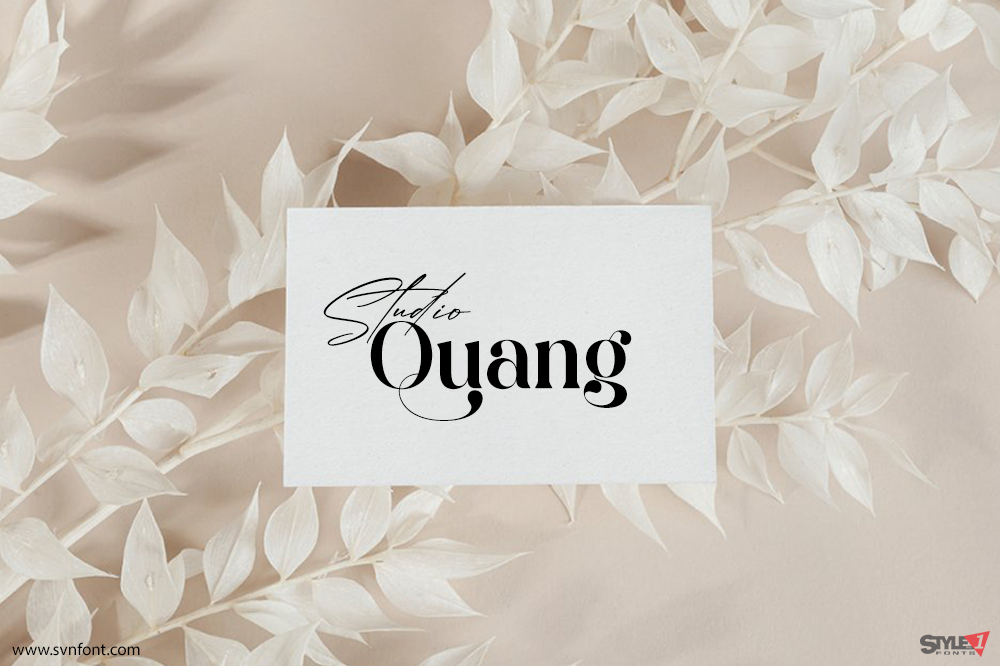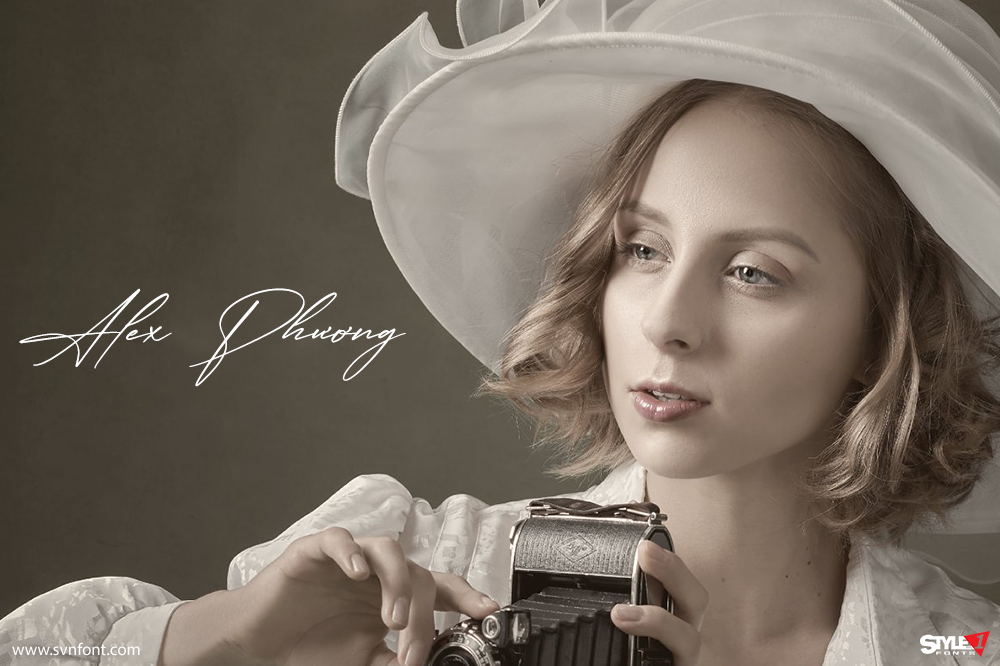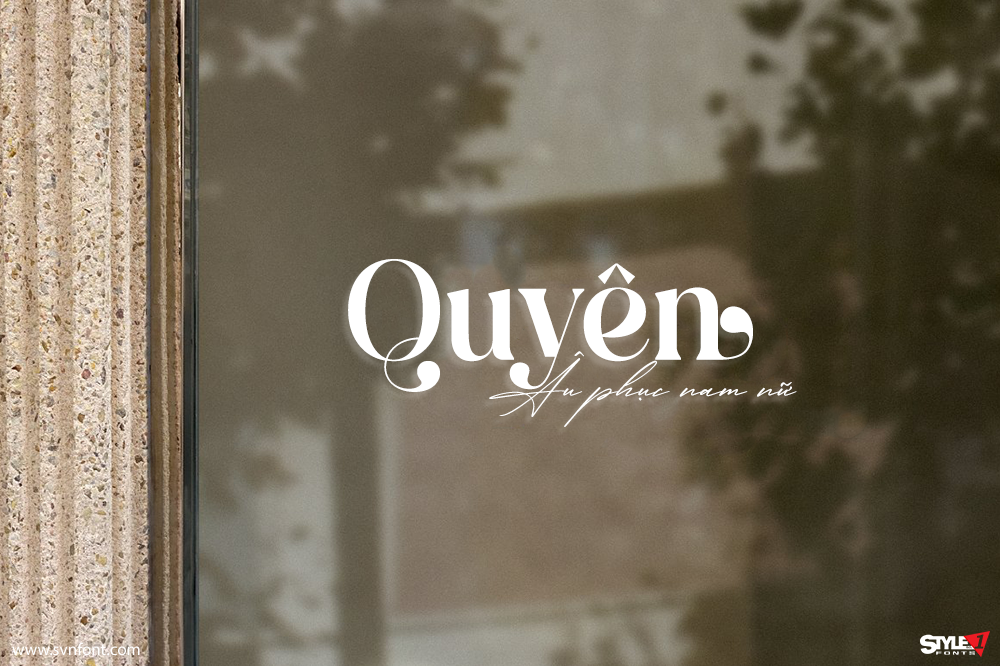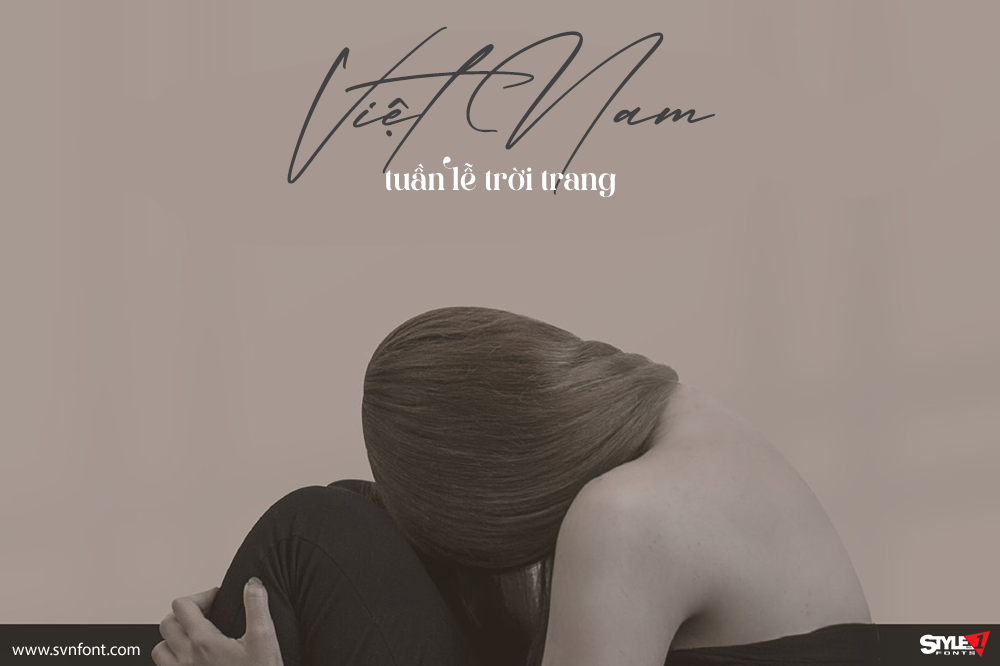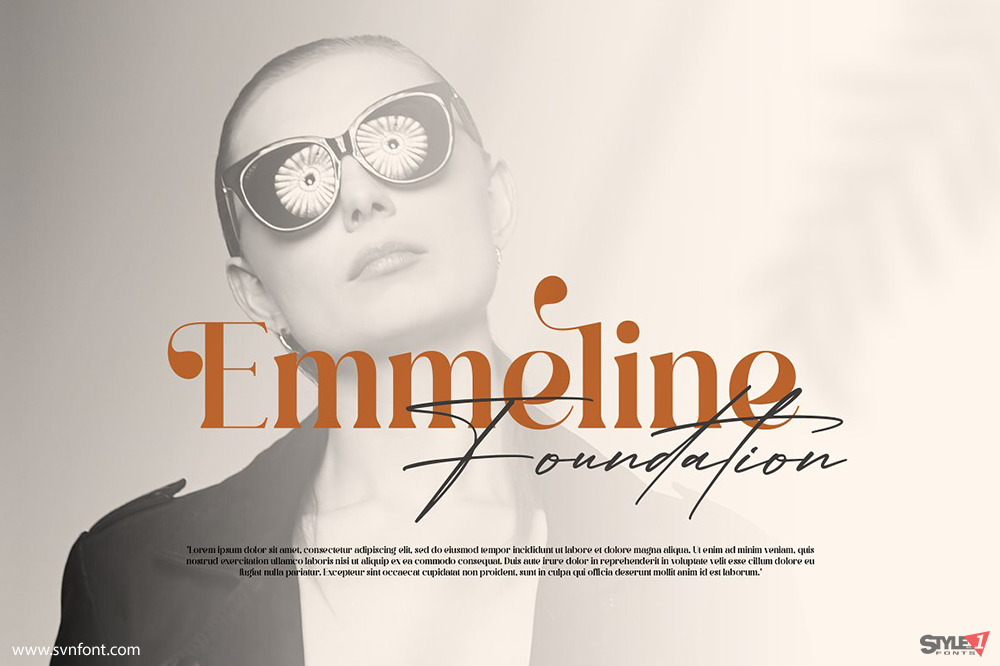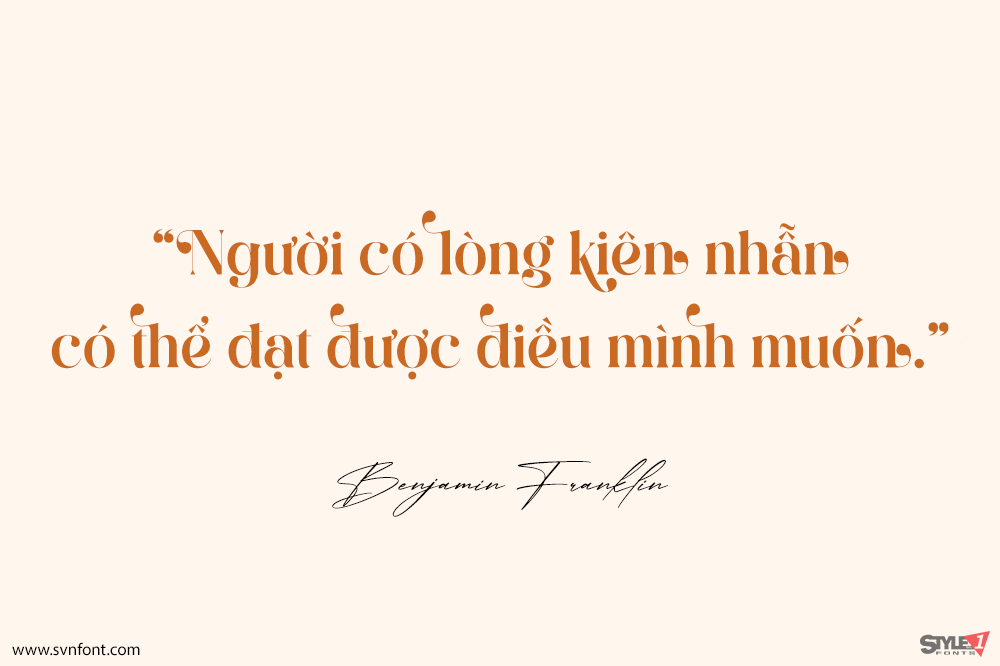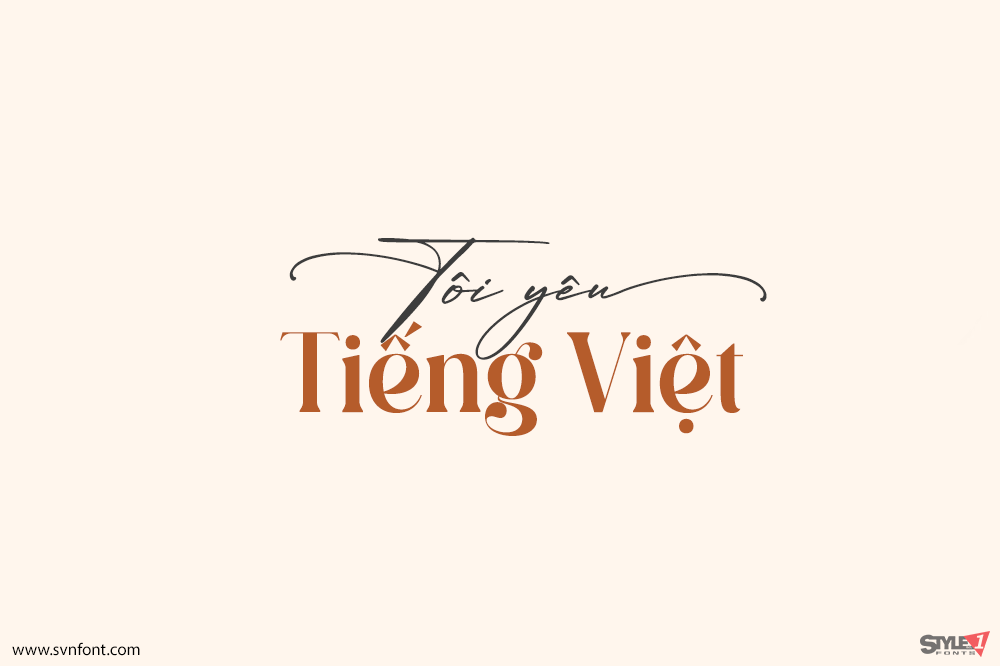
SVN Qalisha - Font chữ Việt hóa kết hợp tuyệt đẹp
Qalisha là một font chữ kết hợp giữa kiểu chữ cổ điển serif và kiểu chữ phong cách chữ ký, phông chữ này mang một kết hợp sẵn với phong cách hiện đại, tinh tế. Kiểu chữ này hoàn hảo cho một logo thanh lịch và sang trọng, thiết kế tiêu đề sách hoặc phim, nhãn hiệu thời trang, tạp chí, quần áo, chữ, trích dẫn, v.v. Nhà thiết kế: Heru Utama Putra Việt hóa: STYLEno.1 Fonts Sử dụng cho cá nhân